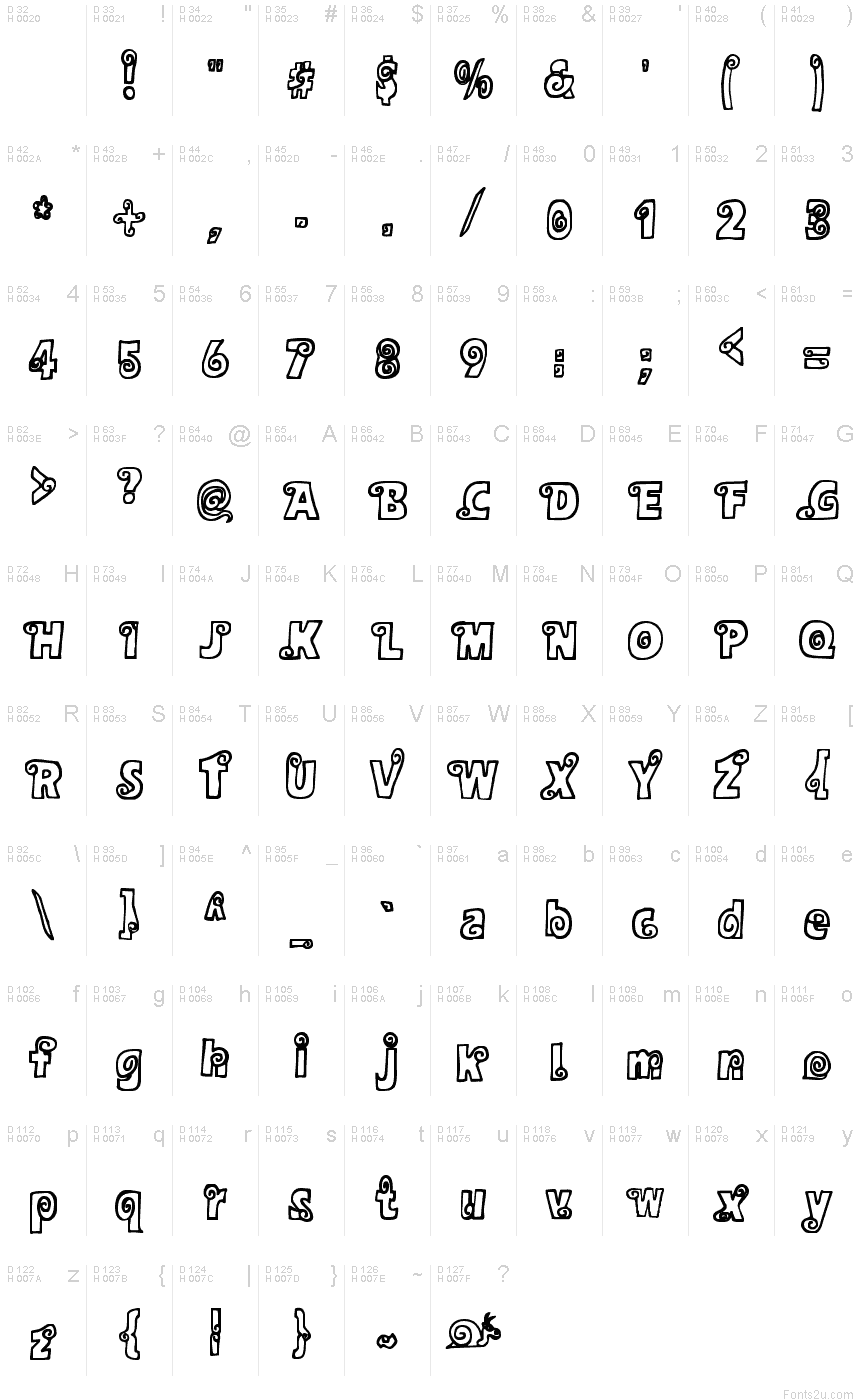
Alphasnail, stworzony przez Phillipa G Andrade, to darmowy krój pisma w stylu cartoon, wyglądający, jakby wyszedł prosto z ręcznie rysowanej książki z bajkami. Każda litera wywija się w ślimakowate spirale i obłe kształty, a tuszowy, nieco „bazgrolony” kontur sprawia wrażenie radosnego, a nie niechlujnego. Luźny, nieco chwiejny rytm nadaje mu dziecięcego uroku, jakby został nakreślony grubym pisakiem na papierze technicznym.
Używając kroju Alphasnail, w mgnieniu oka zmienisz nagłówki w wyjątkowe postacie – świetnie sprawdzi się na okładkach książek dla dzieci, zaproszeniach urodzinowych, plakatach szkolnych, opakowaniach zabawek, banerach imprezowych i zabawnych logotypach. Ten darmowy font najlepiej prezentuje się w większym rozmiarze, gdzie jego zawijasy mogą odetchnąć i zostać w pełni docenione. Spróbuj połączyć Alphasnail z prostym, zaokrąglonym krojem bezszeryfowym w tekście głównym, aby zachować czytelność, podczas gdy litery będą opowiadać własną historię.